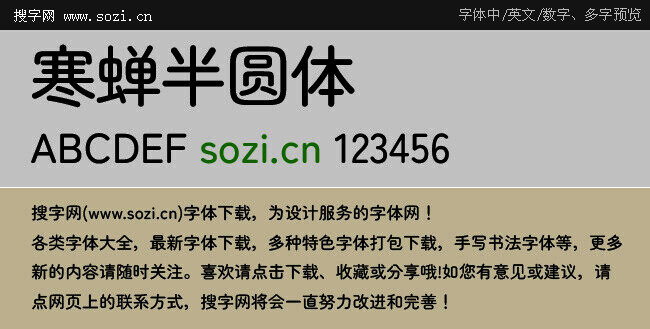
寒蟬半圓體
搜字網(wǎng)提供一款寒蟬半圓體中文藝術(shù)字體下載,寒蟬半圓體是一款基于日本開源字體Zen Maru Gothic進行調(diào)整的圓體字體!更新為符合GB2312標準的字符集,使其應用范圍更廣。修正部分字形和補充部分字形,調(diào)整到更均衡的排版。適合包裝設計、海報設計、廣告設計等應用。